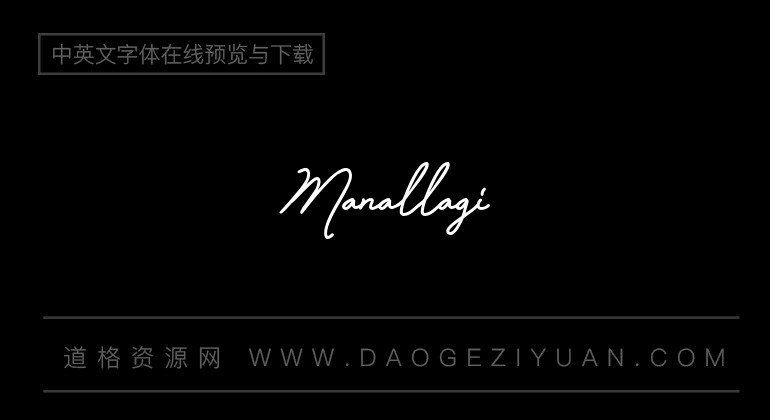
Manallagi
Manallagi是一款简约时尚的英文字体,它具有强烈的视觉冲击力,具有极高的可读性。它以细节为特色,拥有清晰的笔画,给人以精致、简洁的感觉。Manallagi字体适用于广告、标识、海报、书籍封面等设计,能够使设计更加精致、优雅。
Manallagi是一款非常不错的手写艺术字体,具有很好的视觉感,适合于文化类的宣传设计、商业类品牌的广告和产品包装设计以及个性化文字排版等较多场景。